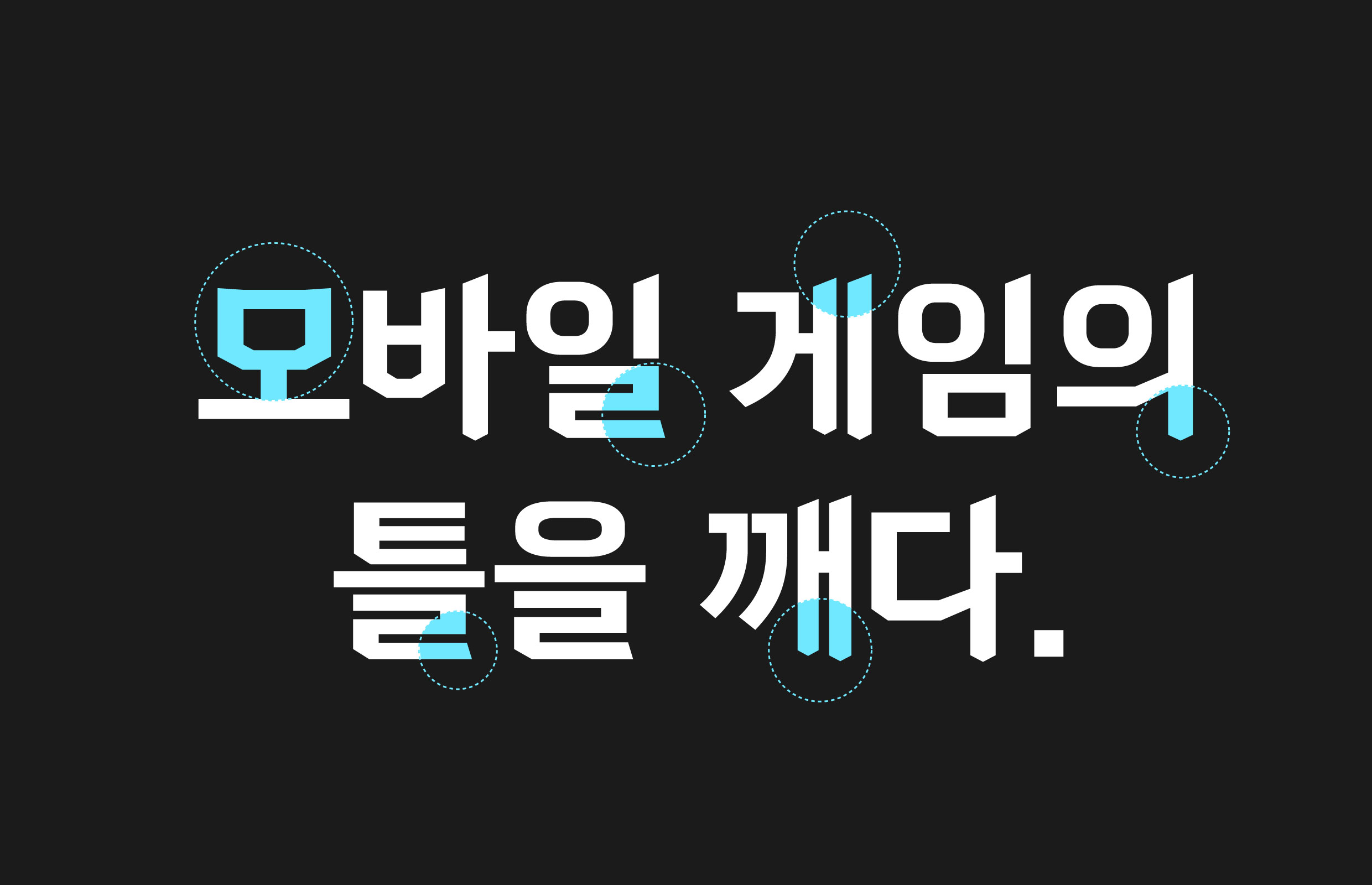
네시삼십삼분
네시삼십삼분 [433검방체]
RPG 게임에서 가장 기본적이고 상징적이라 할 수 있는 전사의 ‘검’과 ‘방패’를 주요한 디자인 요소로 활용한 서체. 한글 자음 ‘ㅁ’과 ‘ㅂ’의 하단 꺾임을 더해 방패의 형태감을 표현했으며, 모음 세로획 하단 단면을 통해 ‘검’을 형상화했다.